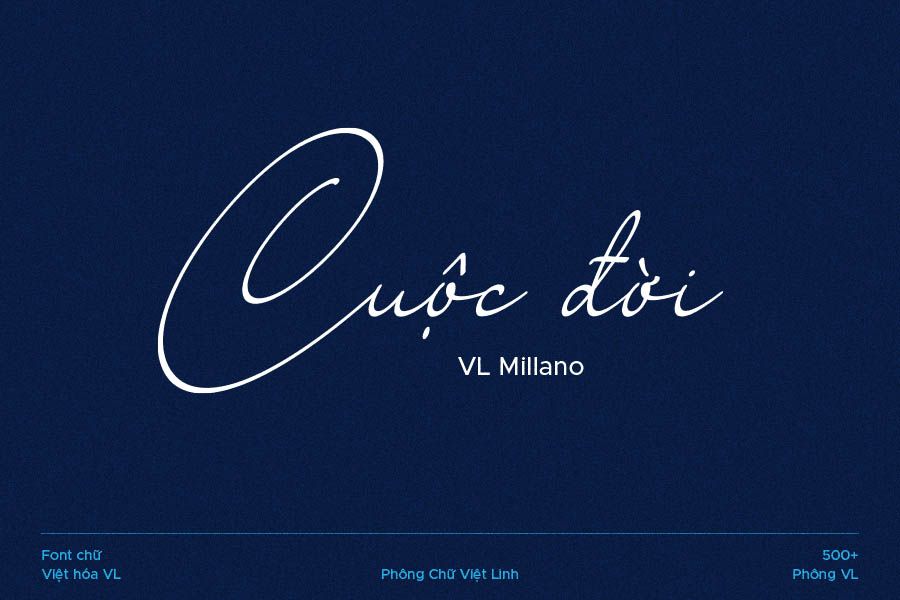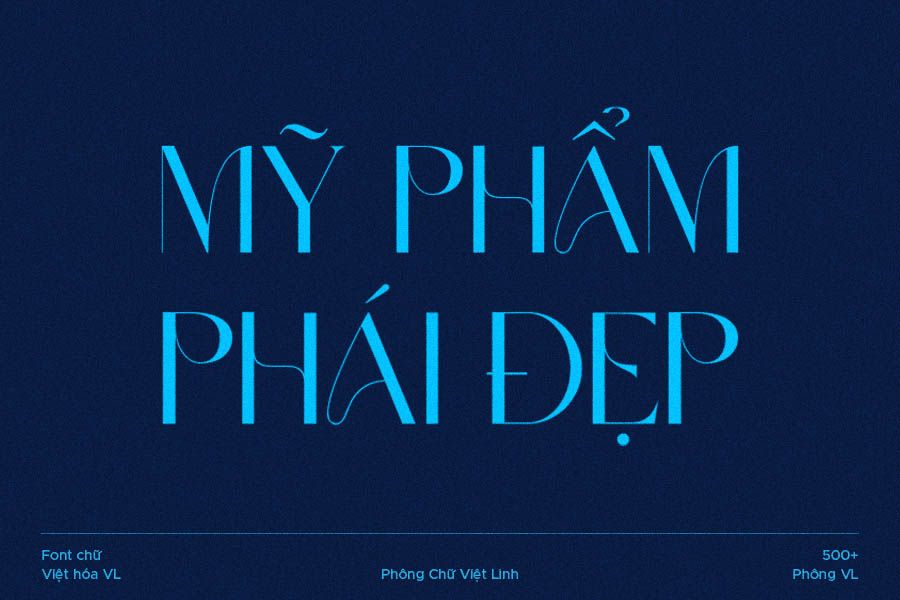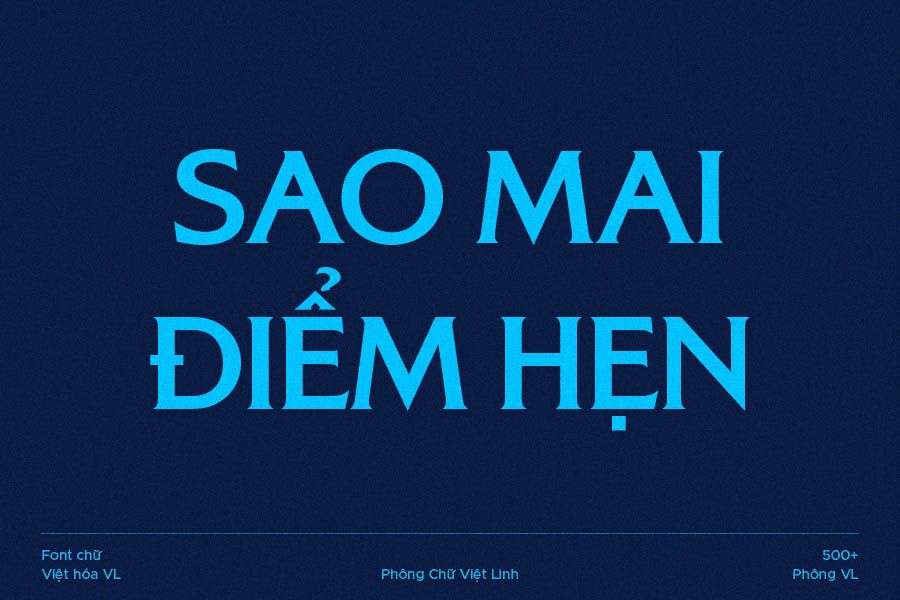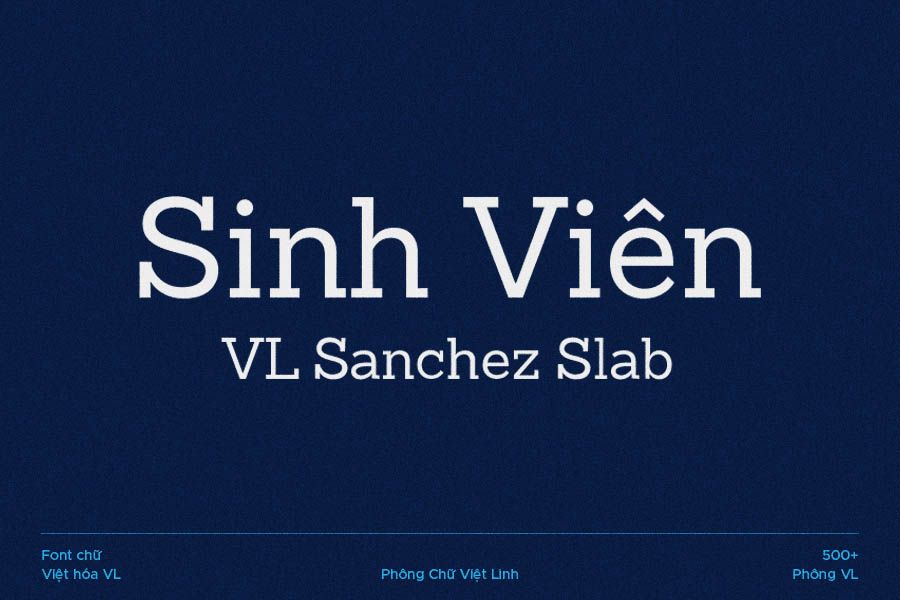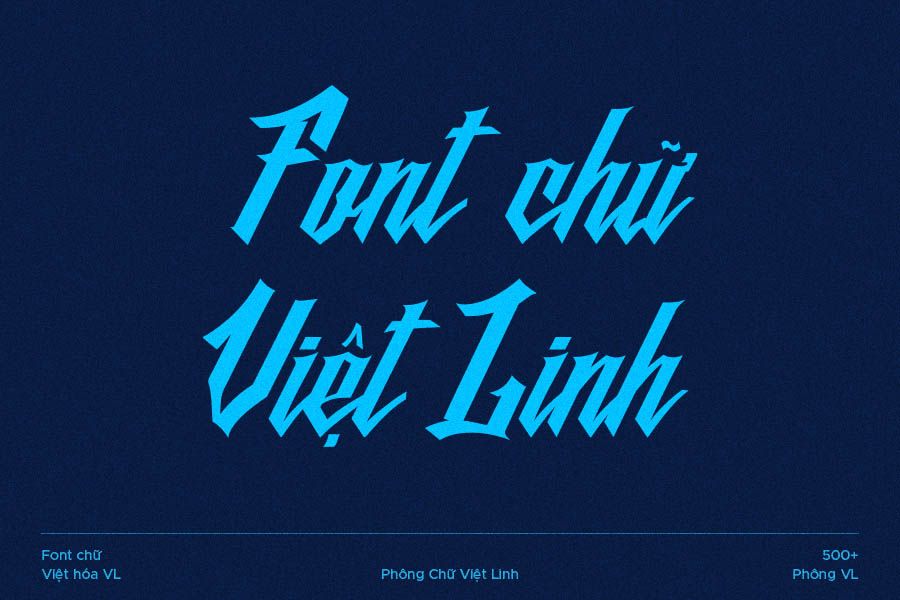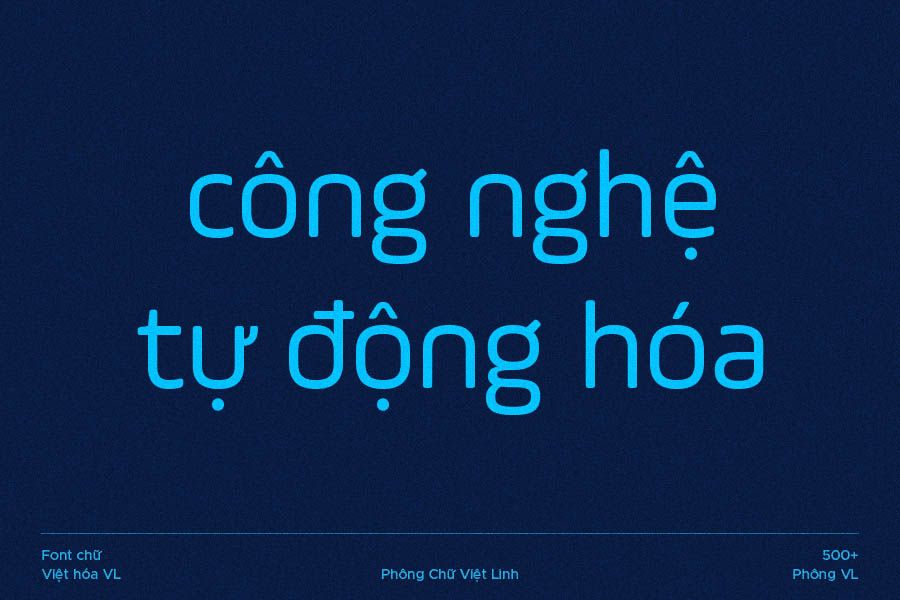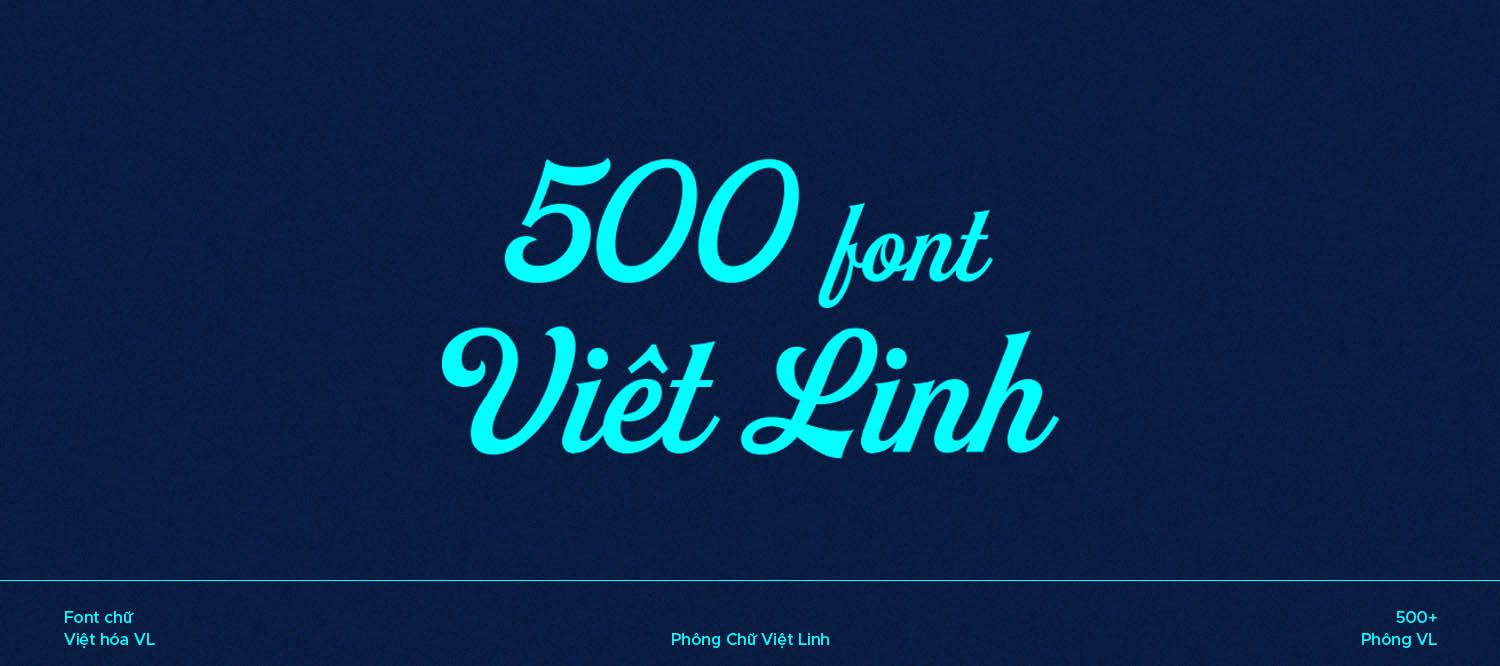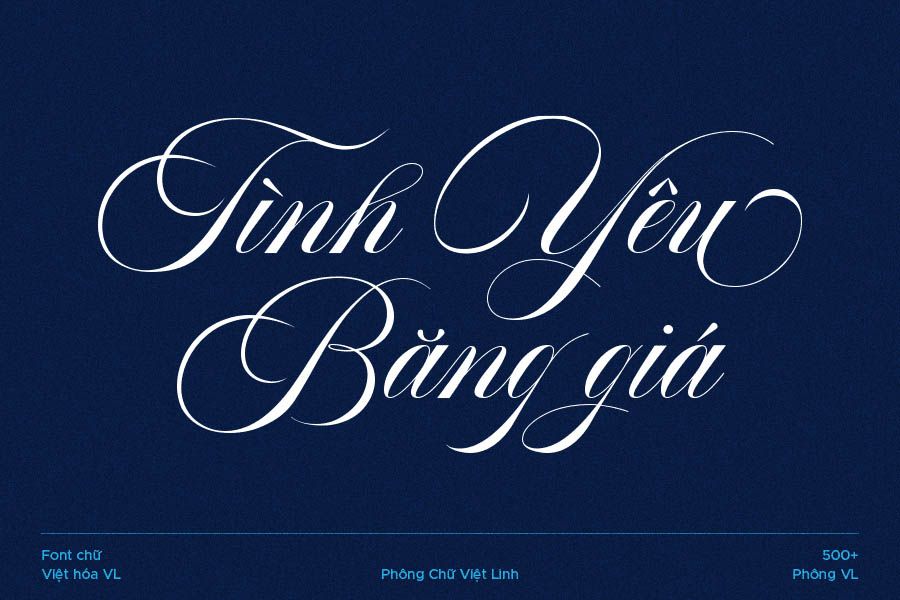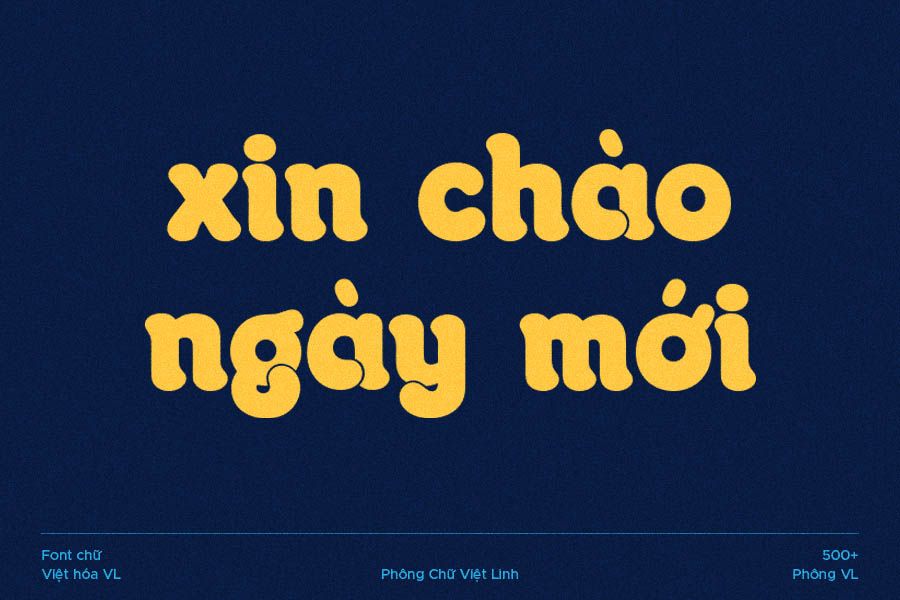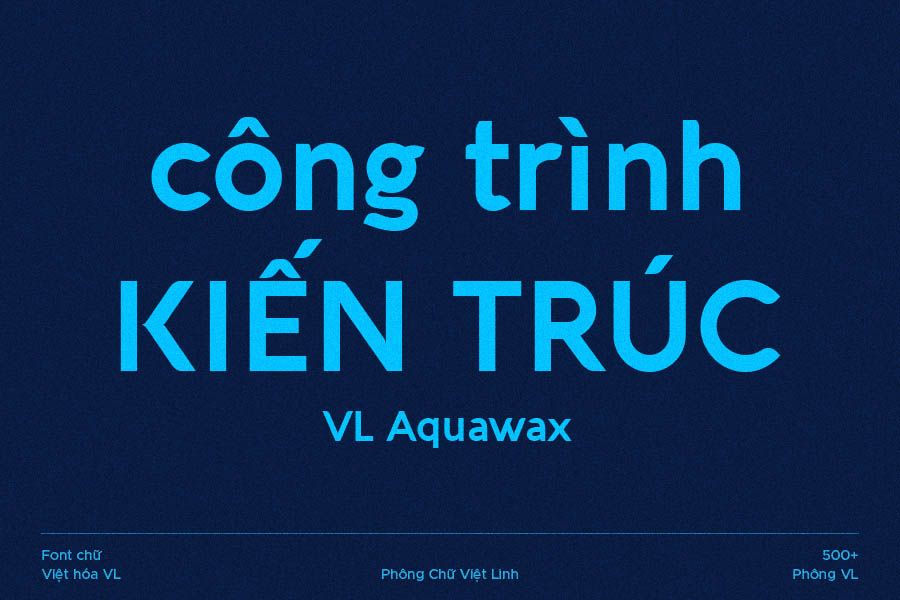
1. Giới thiệu
Trong thiết kế hiện đại, font chữ là yếu tố tạo nên sự khác biệt về mặt thẩm mỹ và cảm xúc. Nếu bạn là designer tại Việt Nam, chắc chắn bạn từng nghe đến Font VL – bộ sưu tập đồ sộ được Việt hóa bởi designer Việt Linh. Với hơn 500 font thuộc nhiều phong cách khác nhau, bộ font này luôn nằm trong danh sách tài nguyên được tải nhiều nhất trên các diễn đàn.
Phiên bản Update 2025 mang đến nhiều cải tiến: bộ dấu tiếng Việt chuẩn hơn, bổ sung nhiều font script và display mới, đồng thời dung lượng tối ưu hơn để quản lý dễ dàng. Đây chính là “kho báu” mà bất kỳ designer nào cũng nên có.
Font chữ VL BlackFuture Việt hóa
Font VL là gì?
“Font VL” là tập hợp các font chữ do Việt Linh Việt hóa. Chữ “VL” chính là viết tắt tên tác giả, xuất hiện ở đầu tên font để người dùng dễ dàng nhận biết. Các font trong bộ đều hỗ trợ Unicode và full dấu tiếng Việt, giúp soạn thảo hay thiết kế không bị lỗi hiển thị.
Việt Linh – người đứng sau bộ Font VL
Việt Linh là một trong những người tiên phong trong phong trào Việt hóa font chữ quốc tế. Từ năm 2010, anh đã bắt đầu chia sẻ những font đầu tiên và dần phát triển thành bộ 500+ font VL hiện nay. Đây là nguồn tài nguyên “quốc dân” của cộng đồng sáng tạo Việt.
Vì sao Font VL được yêu thích?
Có ít nhất 5 lý do khiến Font VL trở thành lựa chọn hàng đầu:
1. Phong phú phong cách – serif, sans-serif, script, display.
2. Hỗ trợ đầy đủ dấu tiếng Việt – không lo lỗi gõ.
5. Ứng dụng linh hoạt – từ branding, poster đến digital marketing.
2. Phân loại Font VL theo phong cách thiết kế
2.1. Font Serif VL – Cổ điển, trang trọng
Font Serif VL mang nét truyền thống với những đường chân chữ tinh tế, tạo cảm giác uy tín và nghiêm túc. Đây là lựa chọn lý tưởng cho sách, báo, tài liệu in ấn hoặc các dự án đòi hỏi sự trang trọng.
Phông chữ miễn phí VL AlexonBold Roman Việt hóa
Font chữ miễn phí VL Monologue Regular Việt hóa
Font VL Belleville07H FY Regular Việt hóa miễn phí
Phông chữ VL Sanchez Slab Việt Hóa
2.2. Font Sans-serif VL – Hiện đại, tối giản
Font Sans-serif VL loại bỏ chi tiết thừa, mang đến sự gọn gàng và dễ đọc. Phong cách tối giản, hiện đại này thường dùng cho thiết kế web, ứng dụng, banner quảng cáo hoặc logo thương hiệu.
Font VL AmpleSoft Việt hóa
Font chữ VL Aquawax Việt hóa
Font chữ VL BrownSugar Việt hóa
2.3. Font Script & Handwritten VL – Lãng mạn, mềm mại
Font Script & Handwritten VL tái hiện nét viết tay mềm mại và bay bổng. Loại font này thường được dùng trong thiệp cưới, bao bì mỹ phẩm, hoặc các thiết kế cần sự lãng mạn và gần gũi.
Font chữ Việt hóa VL Holland
Font Việt hóa VL Millano
Font chữ VL Aston Script Việt hóa
2.4. Font Hoạt Hình VL – Vui nhộn, đáng yêu
Font Hoạt Hình VL có đường nét tròn trịa, vui tươi và bắt mắt, rất phù hợp với các sản phẩm cho trẻ em, truyện tranh, game hoặc thiết kế sáng tạo mang tính giải trí.
Phông chữ hoạt hình VL Chubby Việt hóa
Font chữ VL Octopuss P OT
5. Câu hỏi thường gặp (FAQ)
Font VL có miễn phí hoàn toàn không?
→ Có, nhưng chủ yếu cho mục đích cá nhân.
Font VL có phải chuẩn mực của font Việt hóa không?
→ Không, nhưng đây là bộ phổ biến và ảnh hưởng nhất.
Nhóm font VL nào được dùng nhiều nhất?
→ Sans-serif và Script thường được ứng dụng nhiều trong thương hiệu, thiệp cưới.
Nên chọn Font VL hay Google Fonts?
→ Font VL phong phú và đa dạng hơn; Google Fonts nhẹ và tối ưu hơn cho web.
6. Kết luận
Full Bộ 500 Font VL Việt hóa – Update 2025 không chỉ là kho font đồ sộ, mà còn là “người bạn đồng hành” của mọi designer Việt. Với sự đa dạng, dễ dùng, full dấu tiếng Việt, Font VL giúp bạn sáng tạo thoải mái từ dự án nhỏ đến thương hiệu lớn.
Nếu bạn đang tìm một bộ font “quốc dân” vừa tiện lợi vừa phong phú, thì Font VL chắc chắn là lựa chọn không thể bỏ qua trong năm 2025.